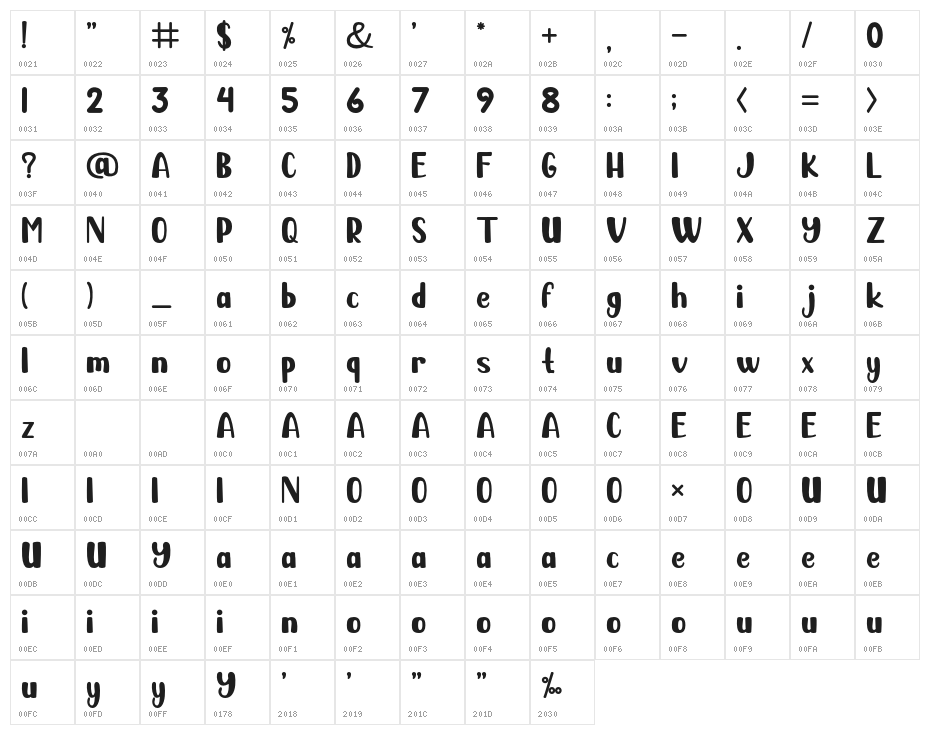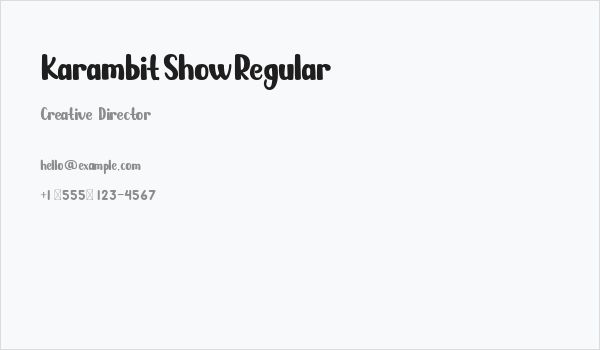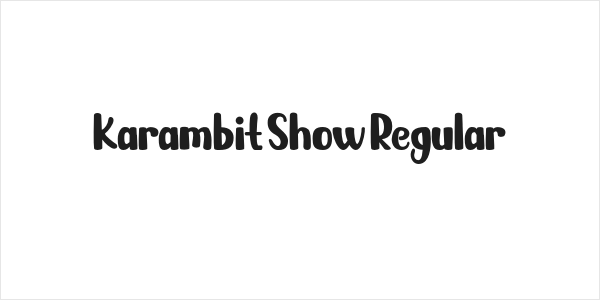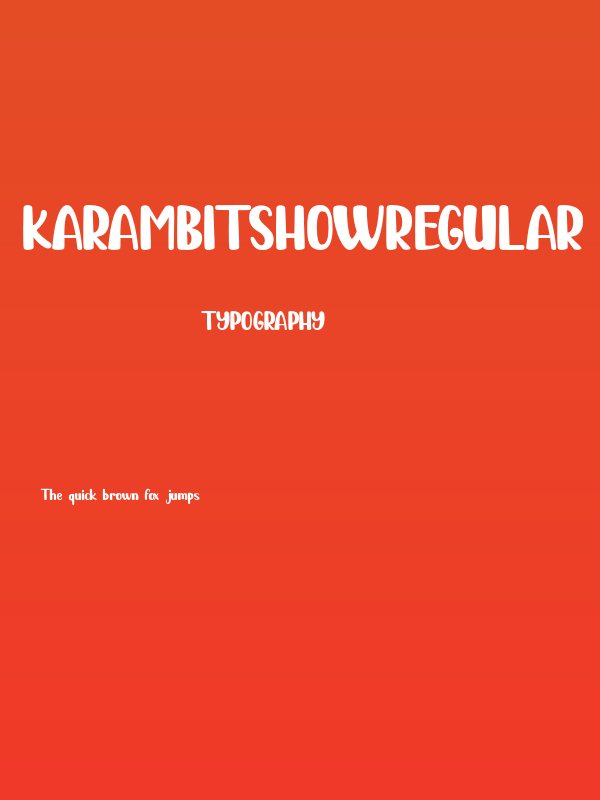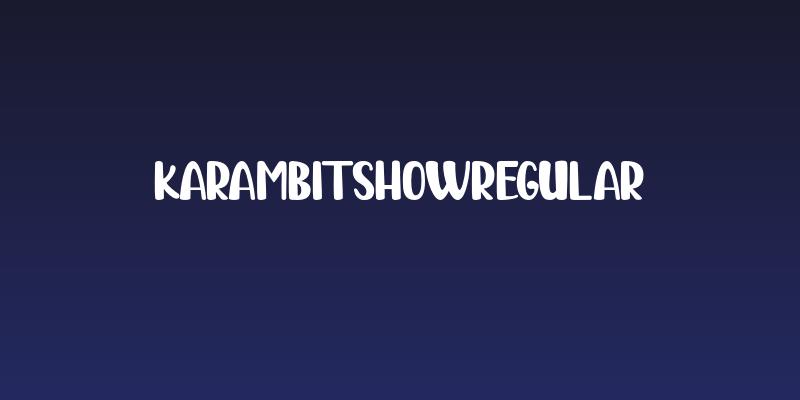
KarambitShowRegular Font
| Gesamtstil | Playful, Hand-drawn |
| Vorgeschlagene Projekte | Ideal for children's books, playful branding, posters, and social media graphics. |